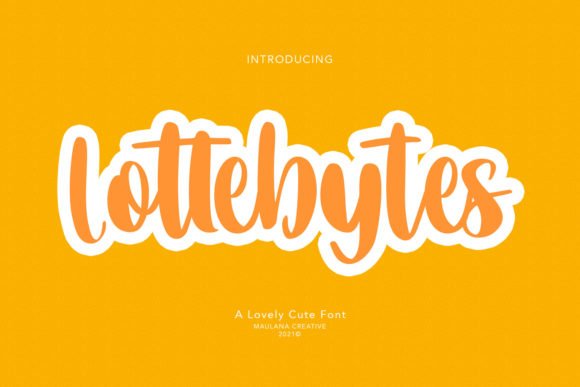
[Creativefabrica] Lottebytes Font (2021)
Lottebytes - это радостный, непринужденный и дружелюбный рукописный шрифт.
Если вы используете его для дизайна, связанного с мультфильмами, детскими играми или просто для любого творчества, требующего милого прикосновения, этот шрифт станет прекрасным выбором.